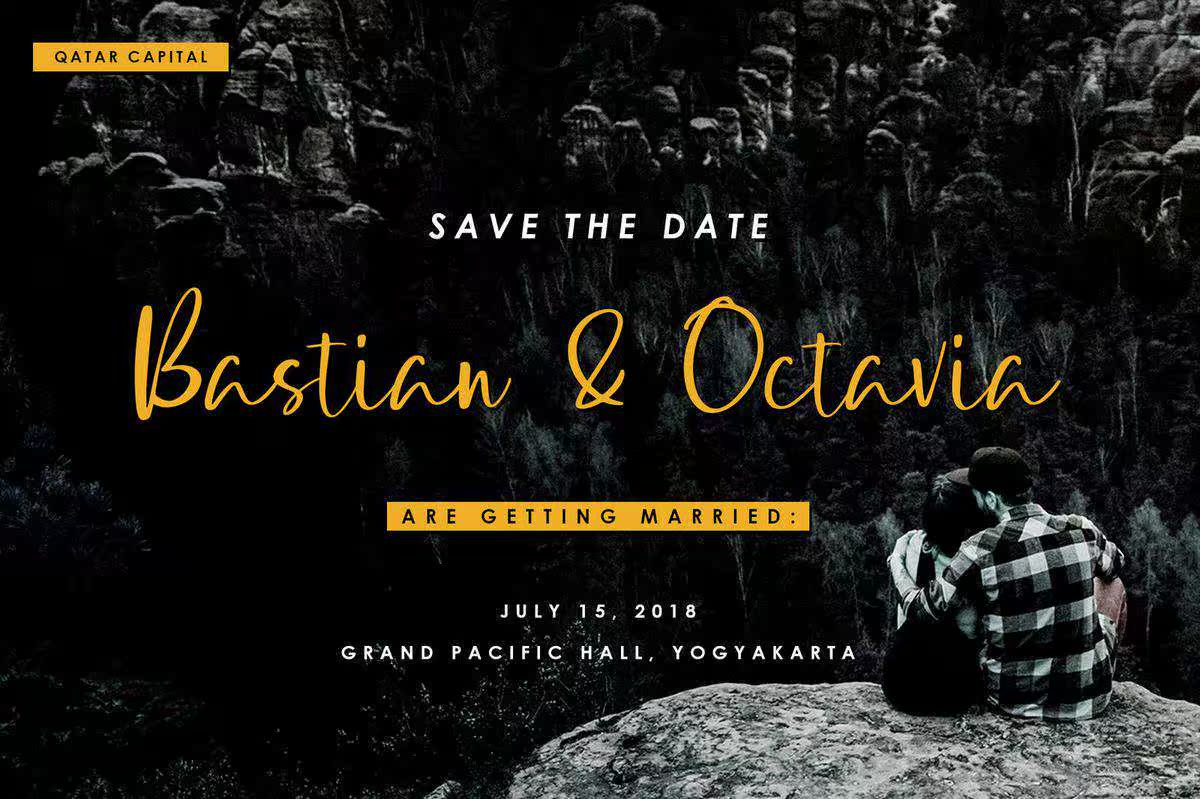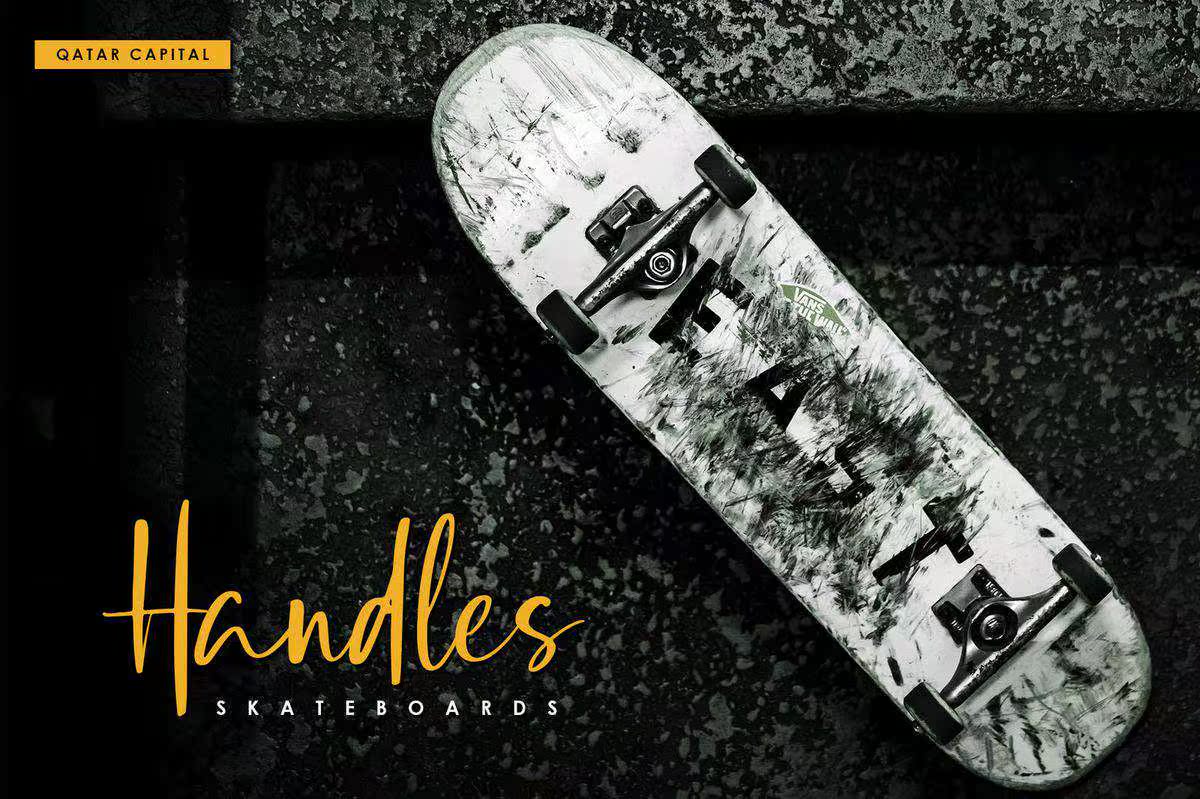
简介脚本字体,卡塔尔首都为手写体,字体为自然和身份验证字体。此字体具有两种样式(常规和塔利克)的真实手写字体效果。每个单独的字体都经过精心起草,以确保您的文本外观美观。简介脚本字体,卡塔尔首都为手写字体,字体为自然和认证字体。该字体采用两种风格(常规和塔利克)的写实手写字体。每个字体都经过精心设计,以确保您的文本外观美观。